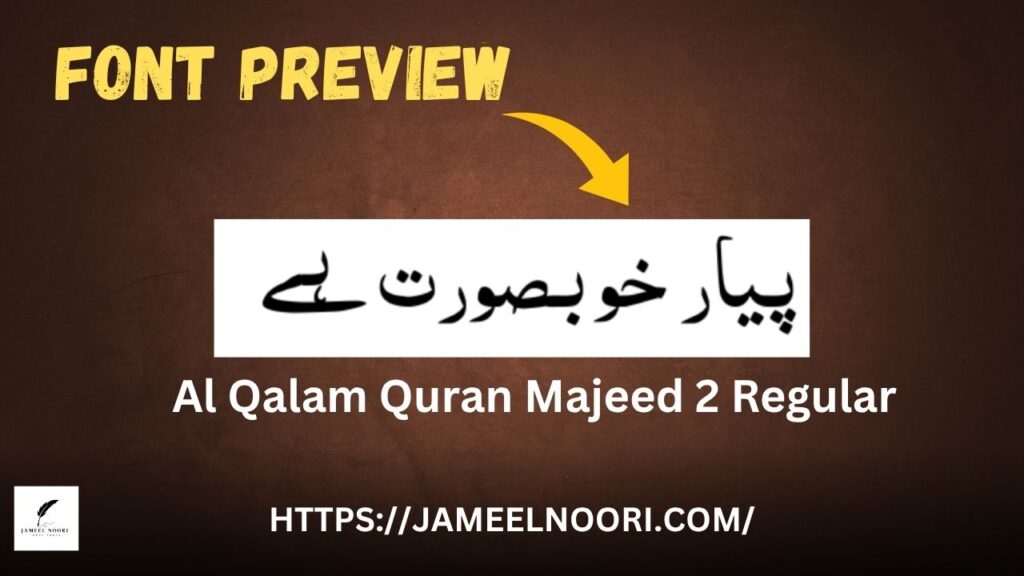
Urdu Font Al Qalam Quran Majeed 2 aik bohot hi popular aur stylish TrueType font hai jo Quranic text likhne ke liye specially design kiya gaya hai. Ye font na sirf readability me behtareen hai balkay Islamic aur professional projects ke liye bhi best choice mana jata hai.
What is Urdu Font Al Qalam Quran Majeed 2?
Urdu Font Al Qalam Quran Majeed 2 aik Regular TrueType font hai jise Quran aur Islamic books likhne ke liye develop kiya gaya. Iska design traditional Arabic calligraphy se inspired hai jisse Quranic text bohot khubsurat aur readable nazar aata hai.
Features of Al Qalam Quran Majeed 2 Urdu Font
Yeh font sirf ek decorative style nahi, balkay readability aur precision dono me perfect hai.
Key features include:
- High-quality Quranic text rendering
- Perfect for Urdu typography and Naskh scripts
How to Use Al Qalam Quran Majeed 2 Urdu Font in Designs
Yeh font specially Islamic designs aur Quranic ayat likhne ke liye best hai.
Why Pakistani Users Love Urdu Font Al Qalam Quran Majeed 2
Pakistan me designers aur students dono ke liye yeh font ek complete package hai.
- Easy to read aur elegant look
- Quranic script ke liye perfect alignment
Is wajah se yeh font Karachi, Lahore aur Islamabad me widely use hota hai.
Benefits of Using Urdu Font Al Qalam Quran Majeed 2 True Type Font
- Professional Quranic display
- TrueType format means clear rendering in print and screen
Urdu Font Al Qalam Quran Majeed 2 un users ke liye best choice hai jo Quranic text ko elegant aur readable form me likhna chahte hain. Iska professional design aur Islamic script style isey Pakistan me har designer aur publisher ka favourite font banata hai.
What type of font is Urdu Font Al Qalam Quran Majeed 2?
It is a Regular TrueType font designed for Quranic and Urdu text.
Does this font support Arabic and Urdu both?
Yes, it supports Arabic, Urdu, and Quranic characters.
Why is this font so popular in Pakistan?
Because of its clear Quranic style and readability.
Who designed Al Qalam Quran Majeed 2 Urdu Font?
It was developed by Al Qalam type foundry, known for Islamic fonts.